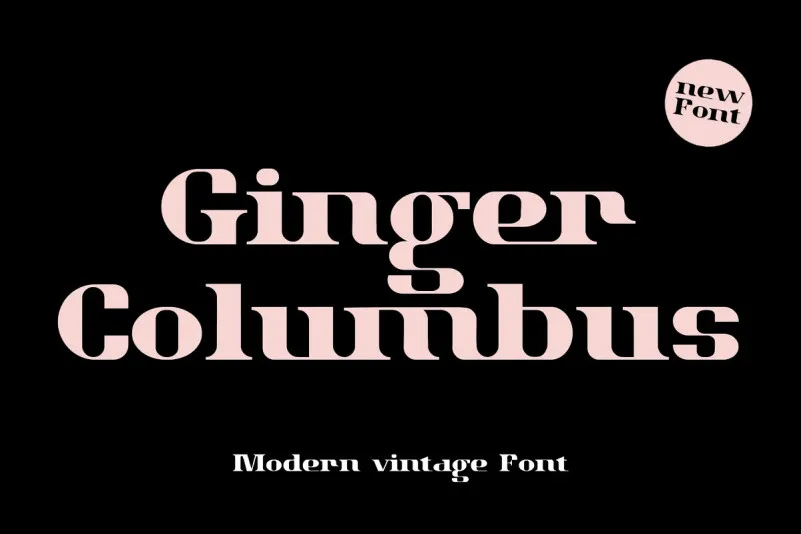
A Ginger Columbus Font é uma tipografia serifada que se destaca por sua contraste acentuado e estilo compacto. Crieada pela Nestype, esta tipografia moderna encaixa-se perfeitamente para temas futuristas ou tecnológicos, combinando elementos do design dos anos 70 com as características modernas da era atual. Suas propriedades versáteis a tornam uma escolha ideal não apenas para projetos arrojados em publicações de revistas ou imagens futurísticas, mas também para invitações ao casamento, branding e até mesmo a criação de painéis ou posters. Ideal tanto para quem busca um tom clássico e sofisticado quanto para aqueles que desejam uma iluminação moderna e inovadora em seus projetos. Combinando elementos do passado com a contemporaneidade, esta fonte oferece uma variedade incrível de opções para qualquer projeto visual.